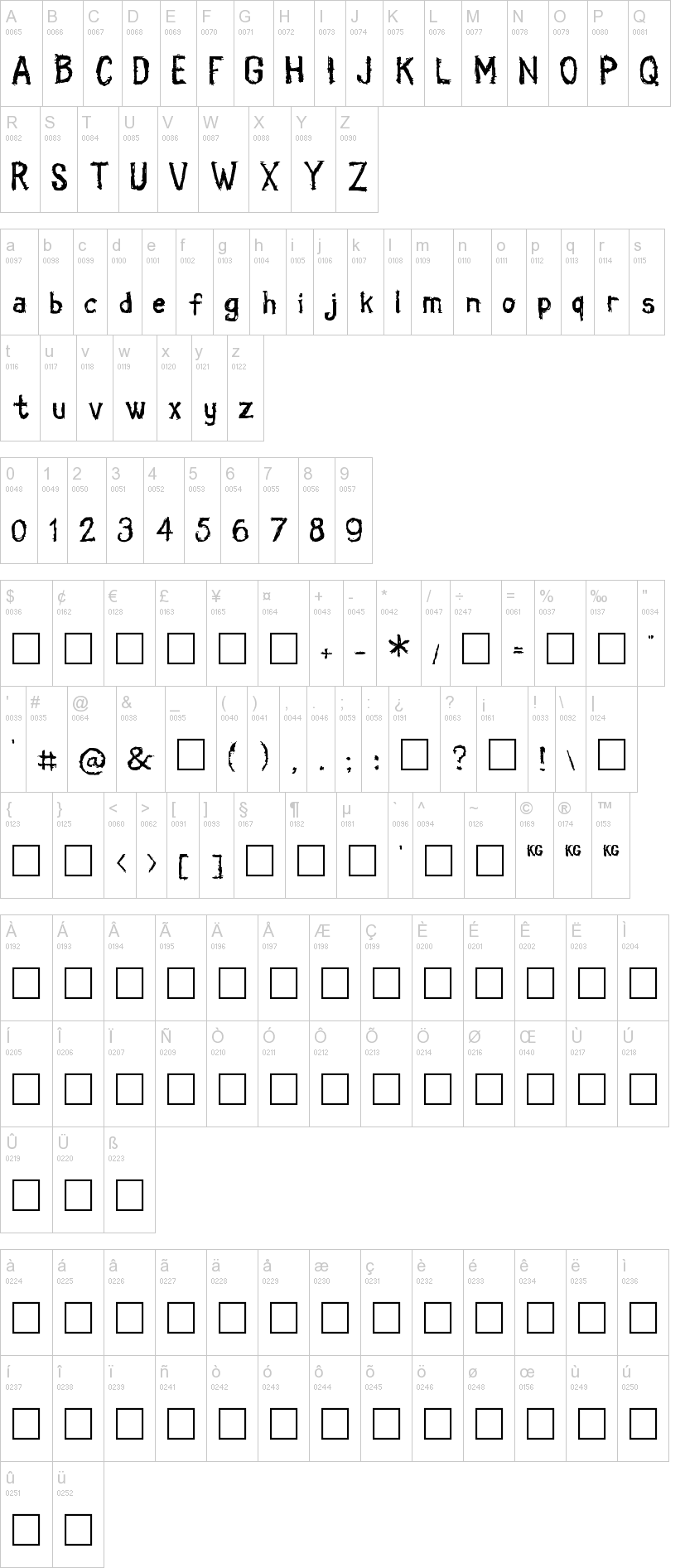
Coldbringer KG 是由设计师 Kimberly Geswein 创建的一种手写字体。该字体具有清晰的线条和坚实的笔画,适用于设计海报、标志、展示等。该字体的特点是字母形状不规则,带有一些有机的感觉,但整体看起来非常清晰和可读。Coldbringer KG 可以在商业和个人项目中免费使用,可在 Kimberly Geswein 的网站上下载。内容介绍
Coldbringer KG是一款非常不错的手写艺术字体,具有很好的视觉感,适合于文化类的宣传设计、商业类品牌的广告和产品包装设计以及个性化文字排版等较多场景。